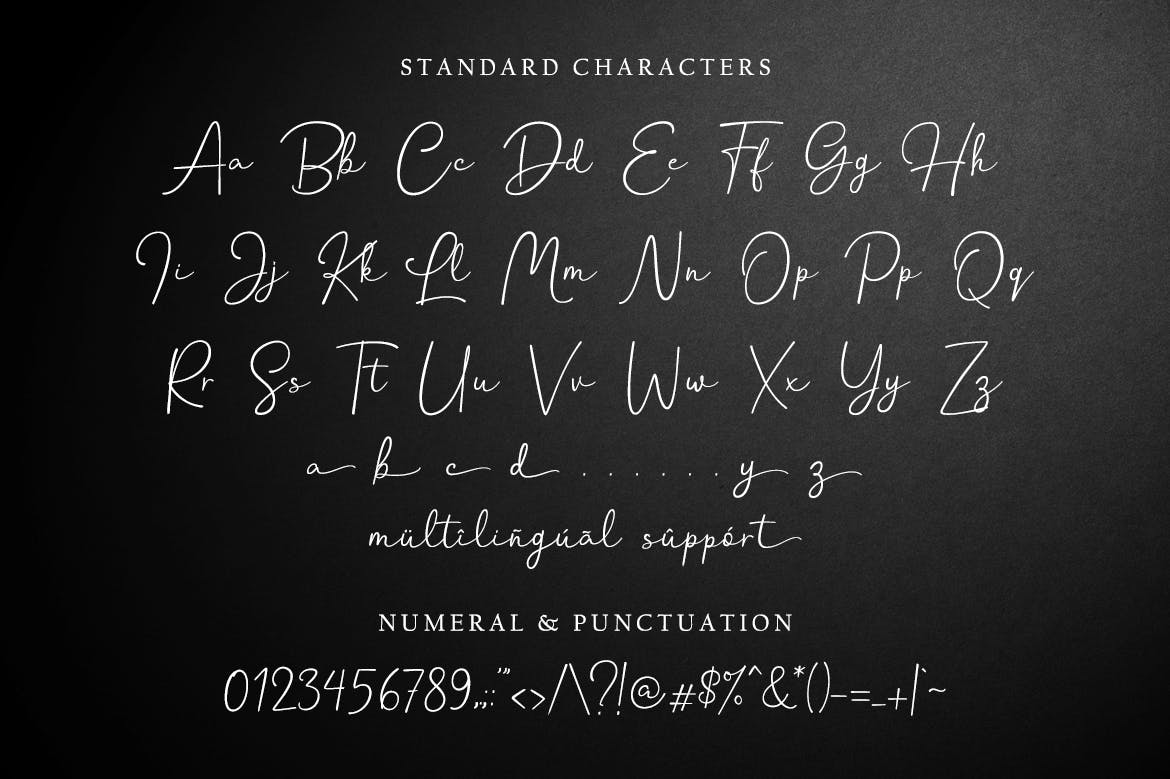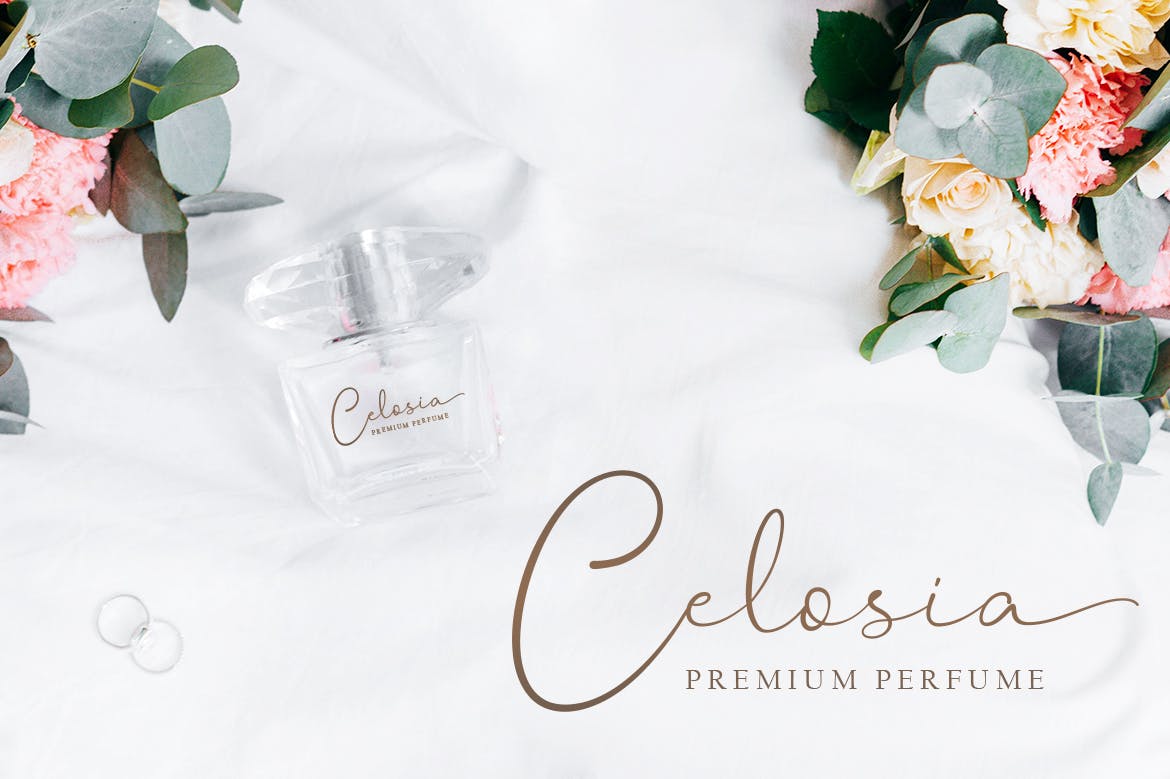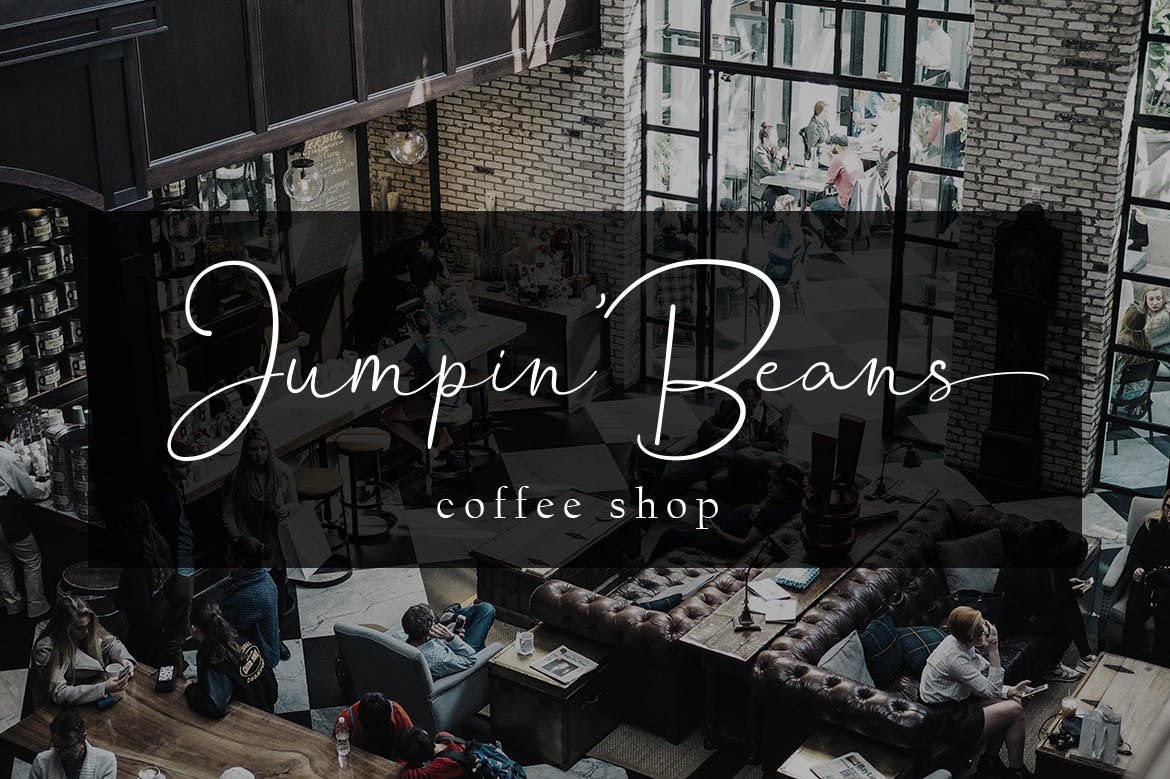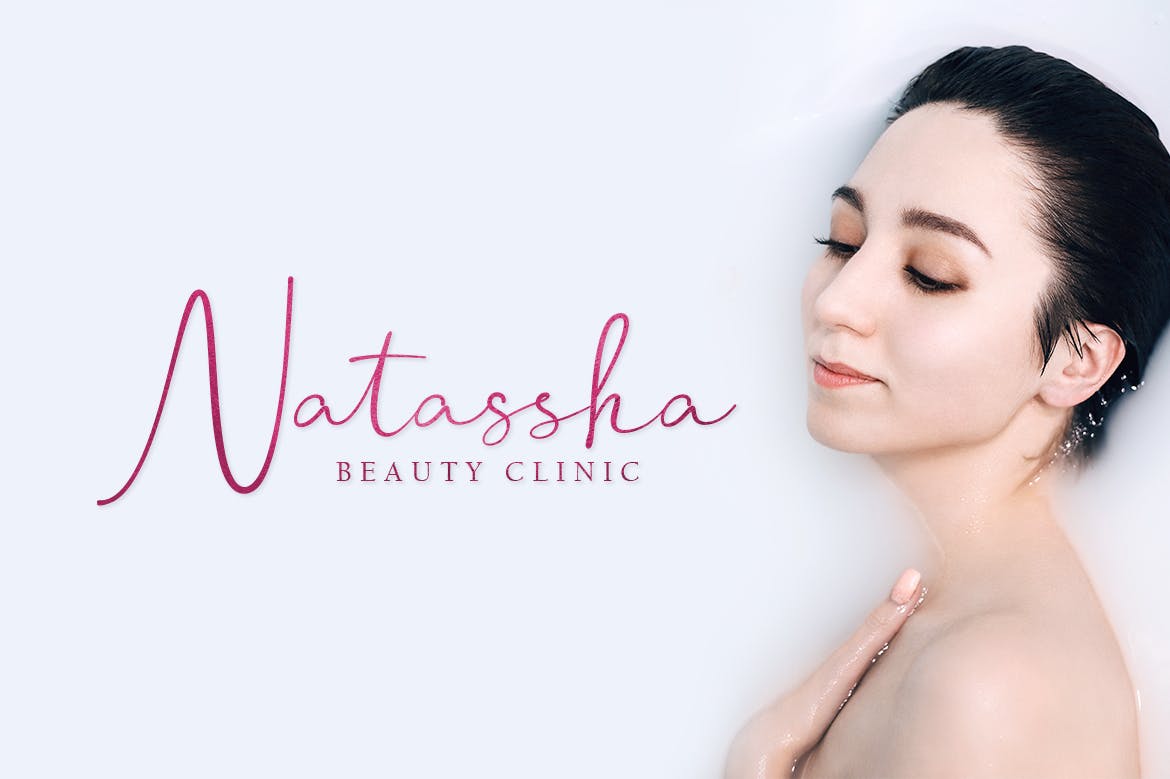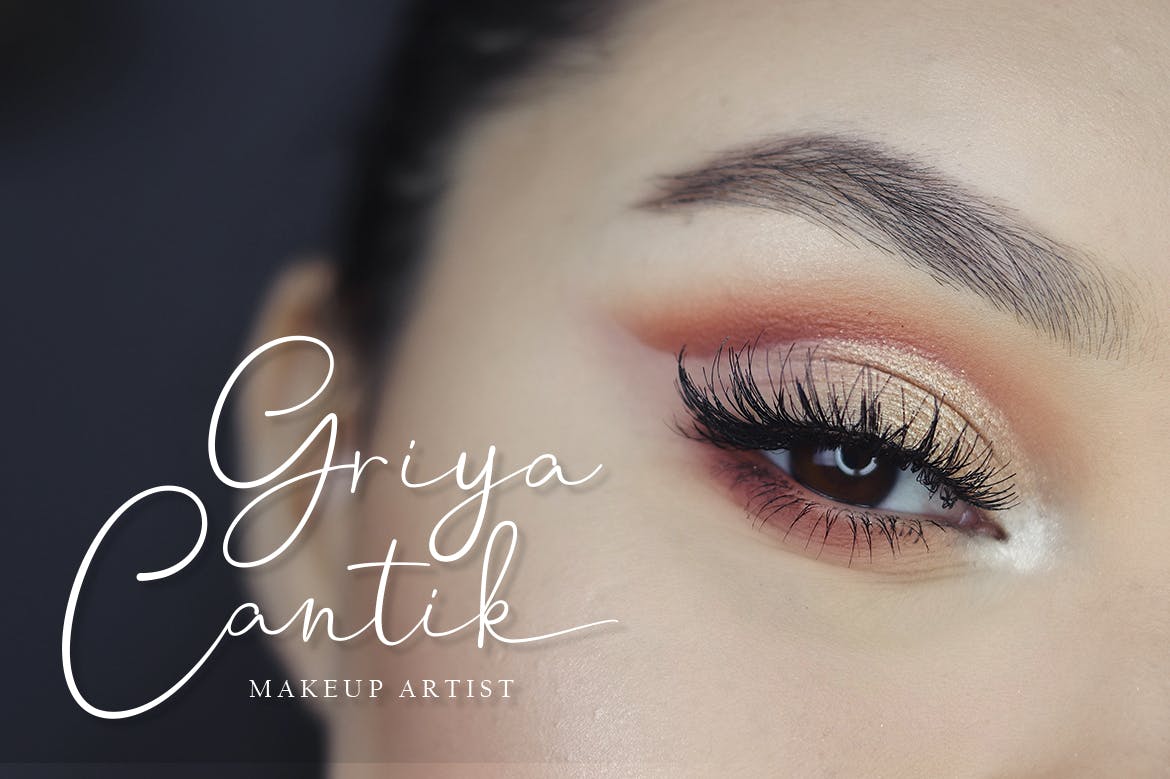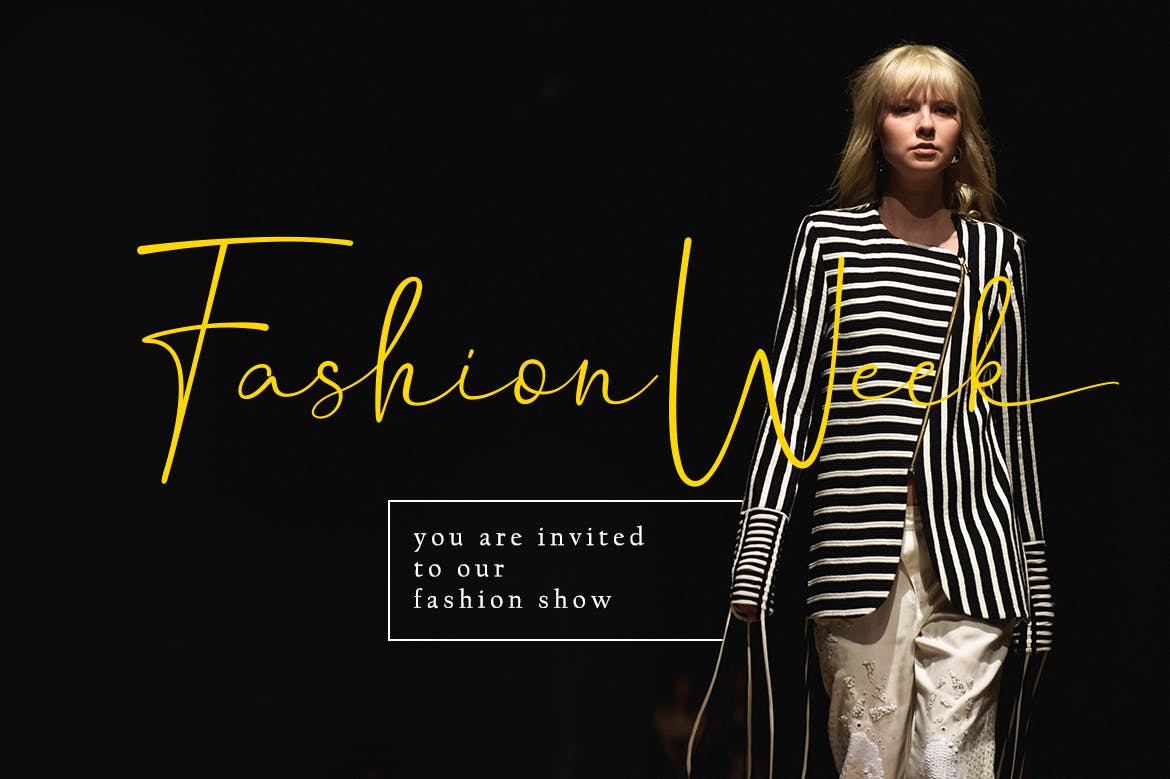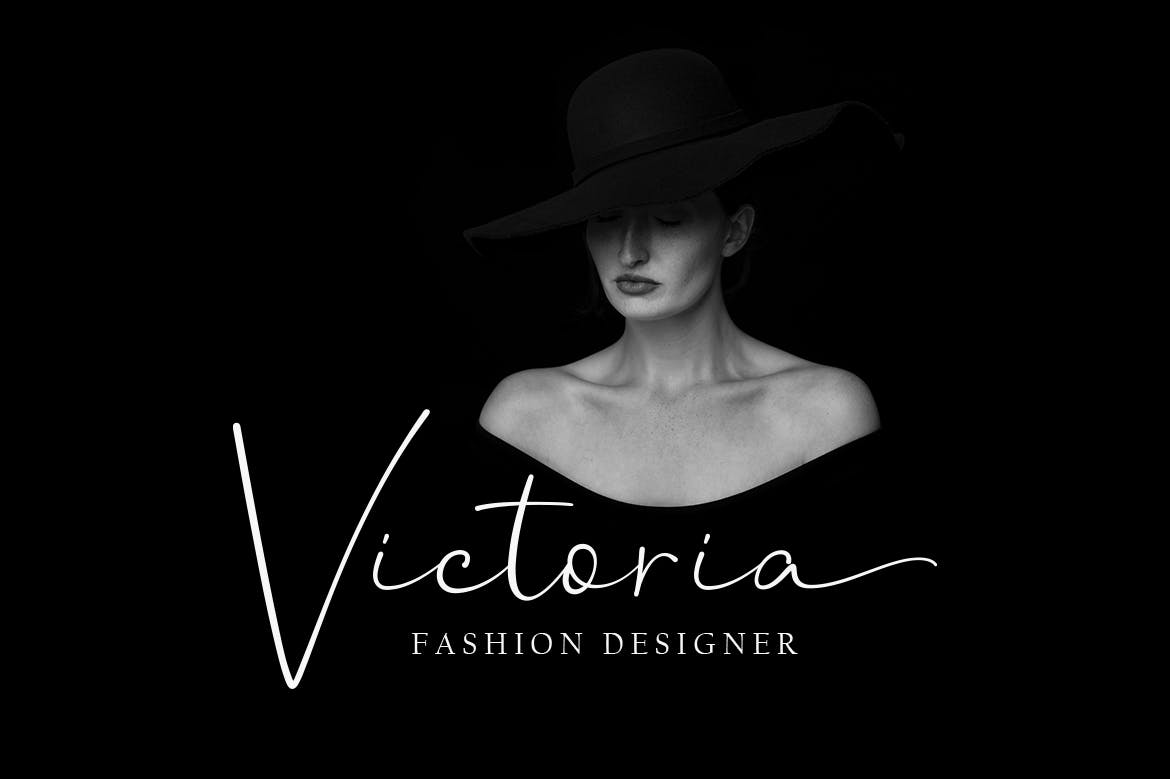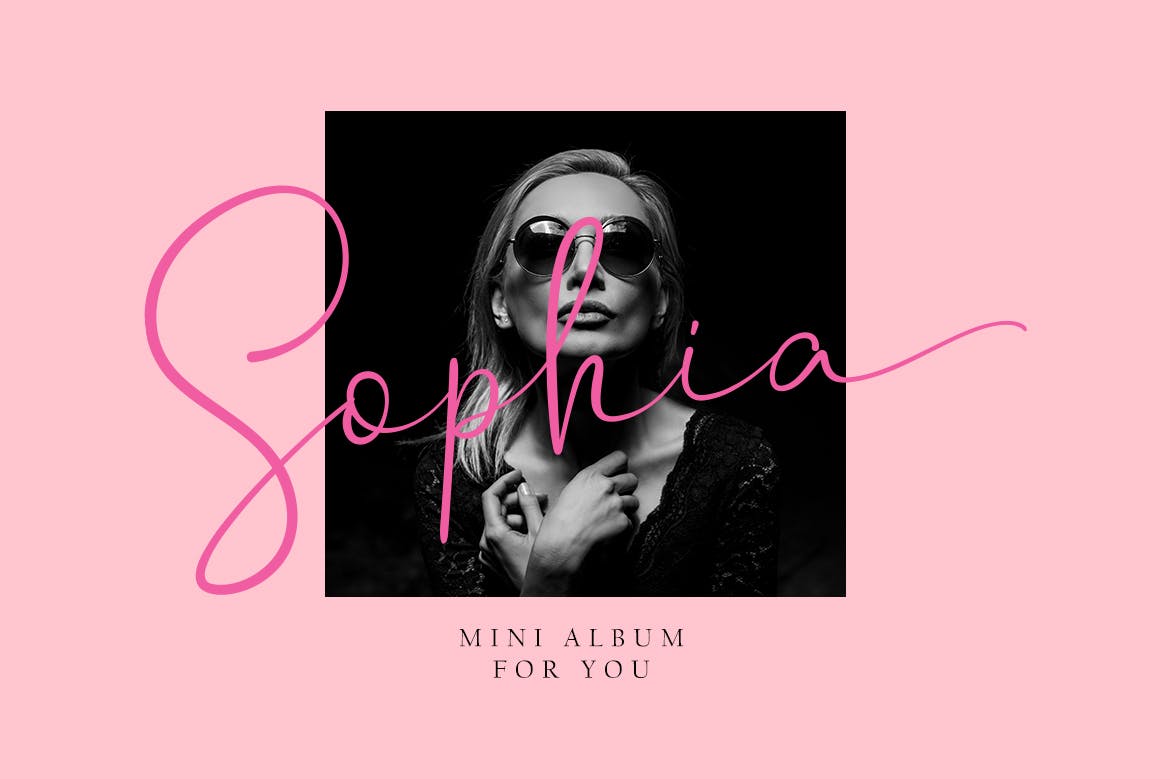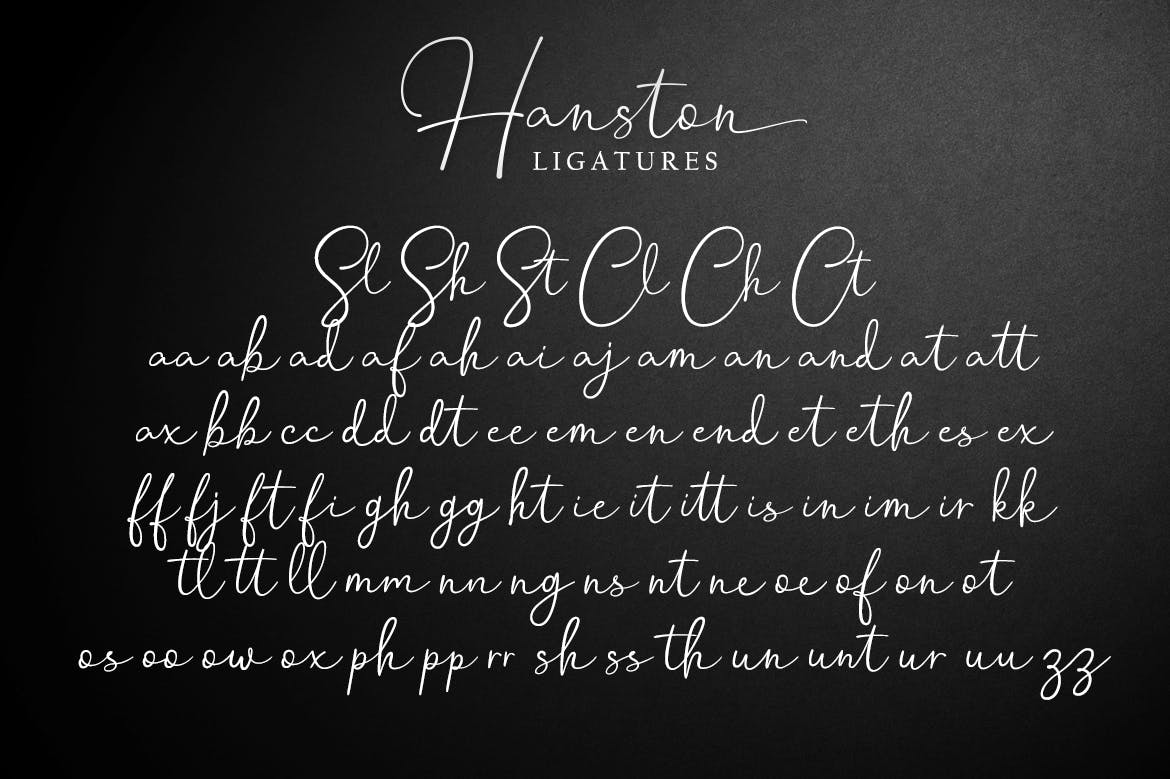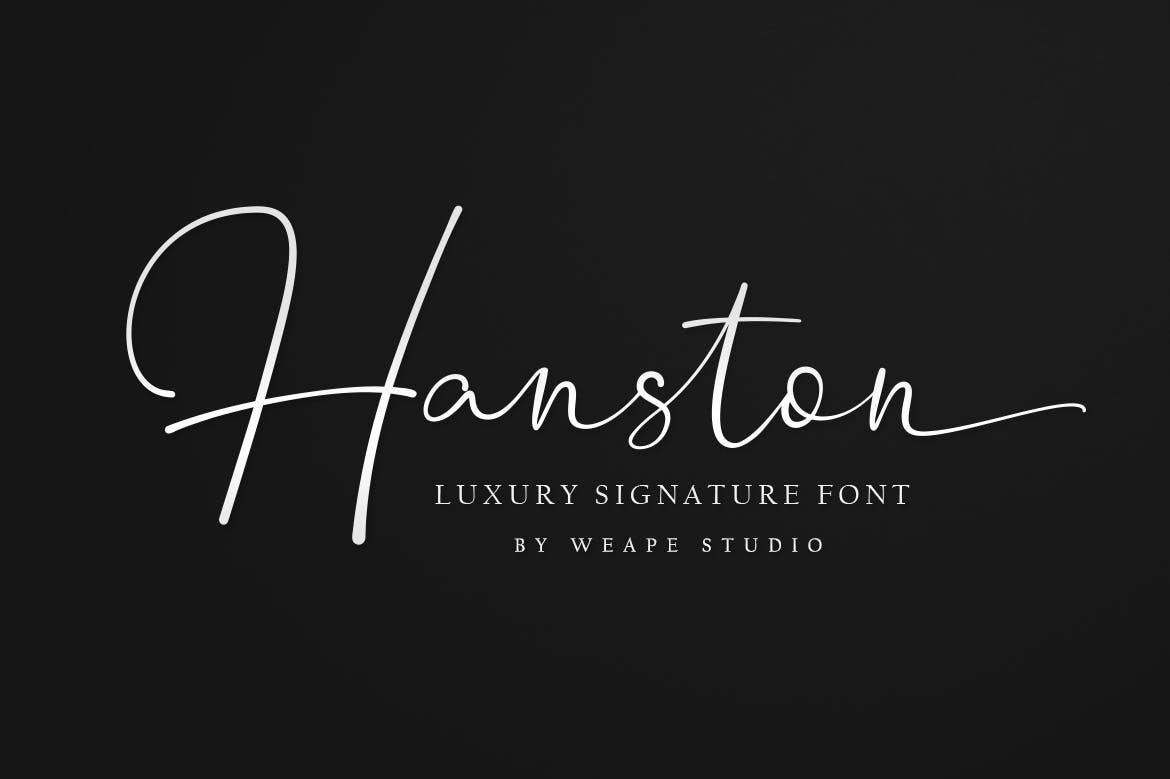
معرفی فونت لوکس هانستون.
این فونت با لمسی از هنر خوشنویسی مدرن، برای زیباسازی هر جملهای که نوشته میشود، بسیار مفید است.
هانستون با ویژگیهای اوپنتایپ طراحی شده و شامل تعداد زیادی لیگاتور و سوآش در انتها است که آن را طبیعیتر و شبیه به نوشتن دستی میکند.
با وجود لیگاتورهای متنوع، این فونت تنوع بیشتری را به ارمغان میآورد. سبک خوشنویسی مدرن آن برای نیازهای روزمره و پروژههای شما مناسب است، از جمله: لوگو، مد، برچسب، واترمارک عکاسی، نقل قولها، هدر بلاگ، پوستر، عروسی، دعوتنامه، لوازمالتحریر، برندینگ، نامه و غیره.